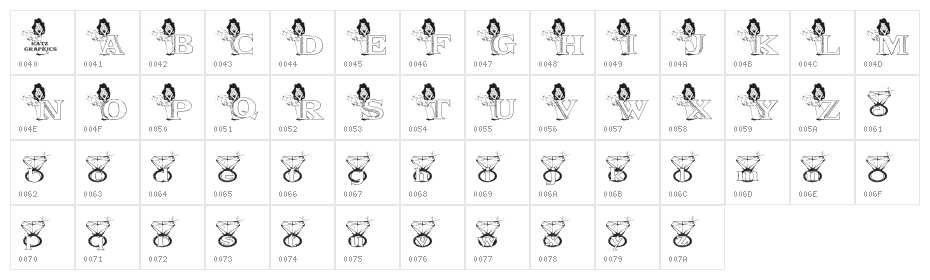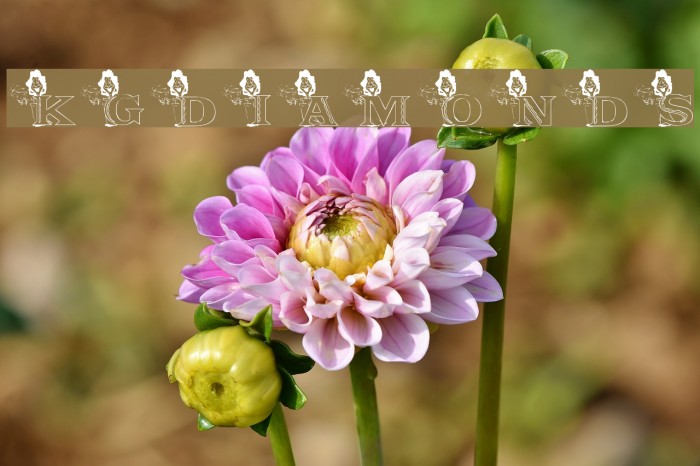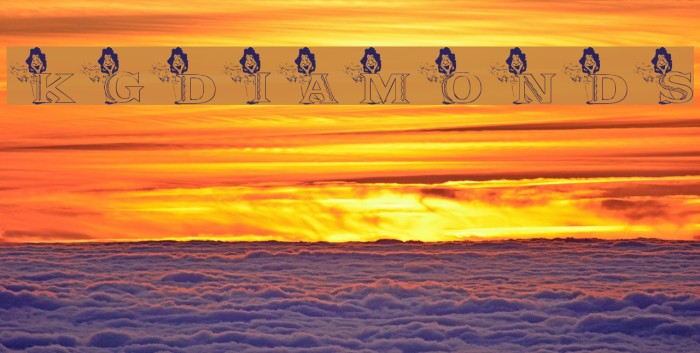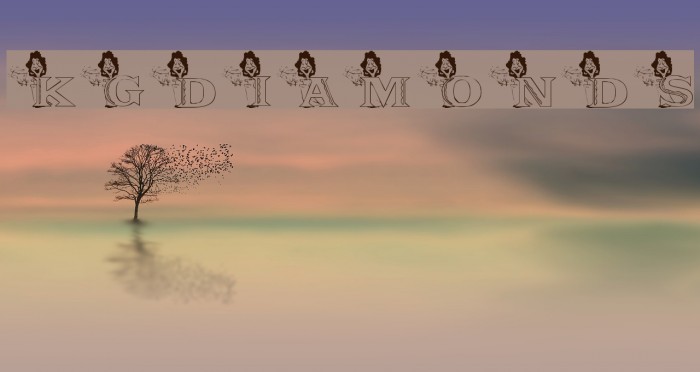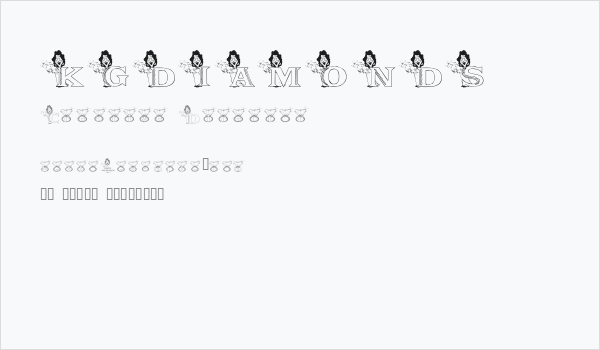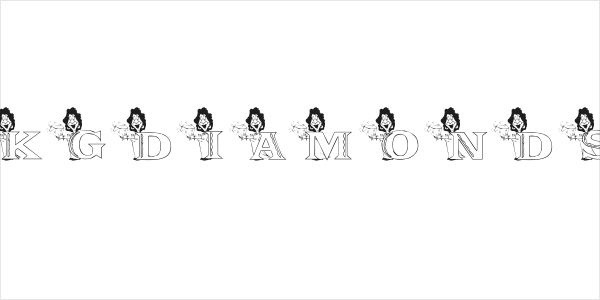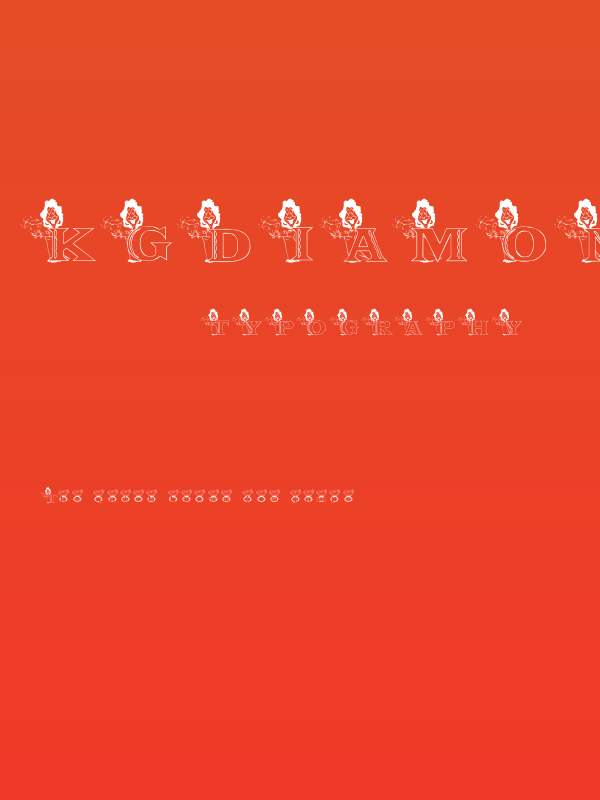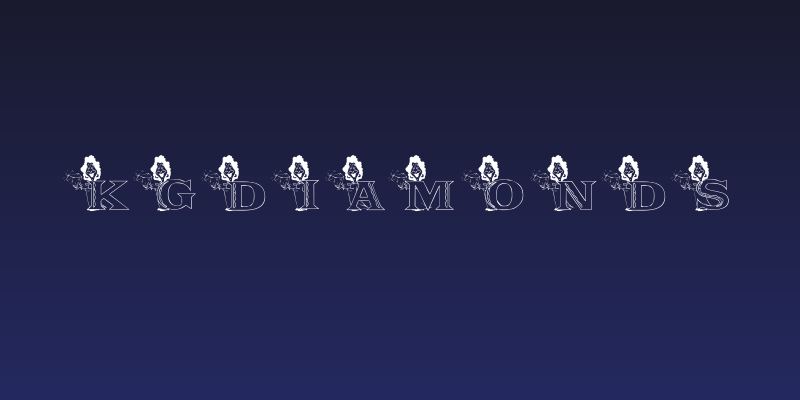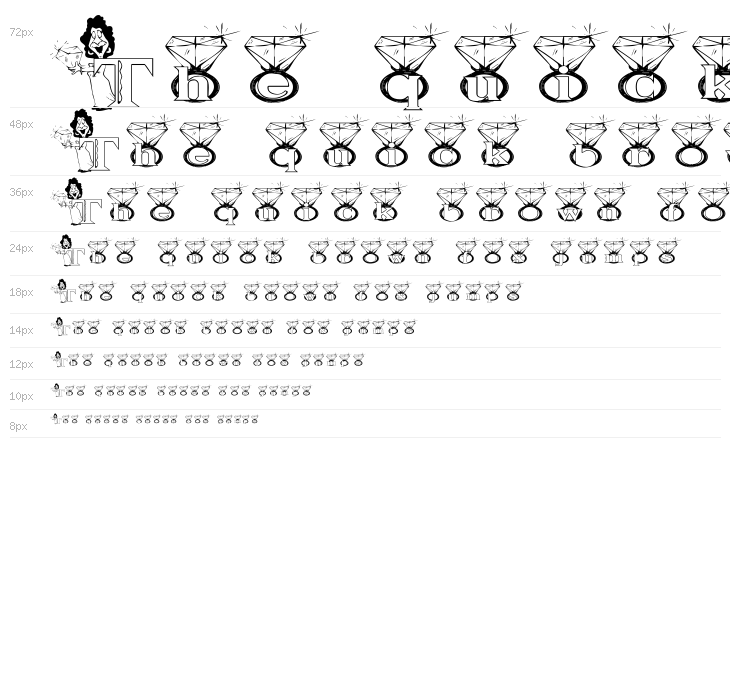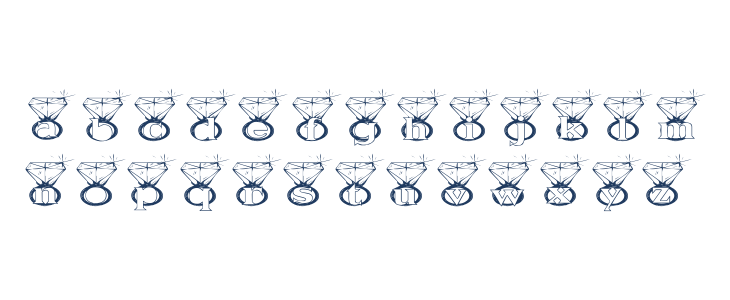
KGDIAMONDS Font
| Cas d'utilisation | Logos, Headlines, Invitations |
| Projets proposés | Ideal for wedding invitations, jewelry branding, luxury event promotions, and decorative headlines. |